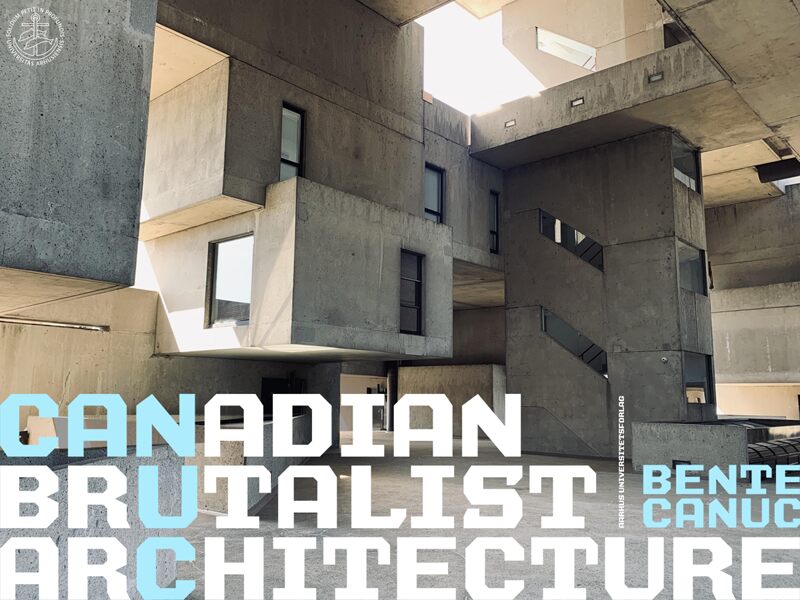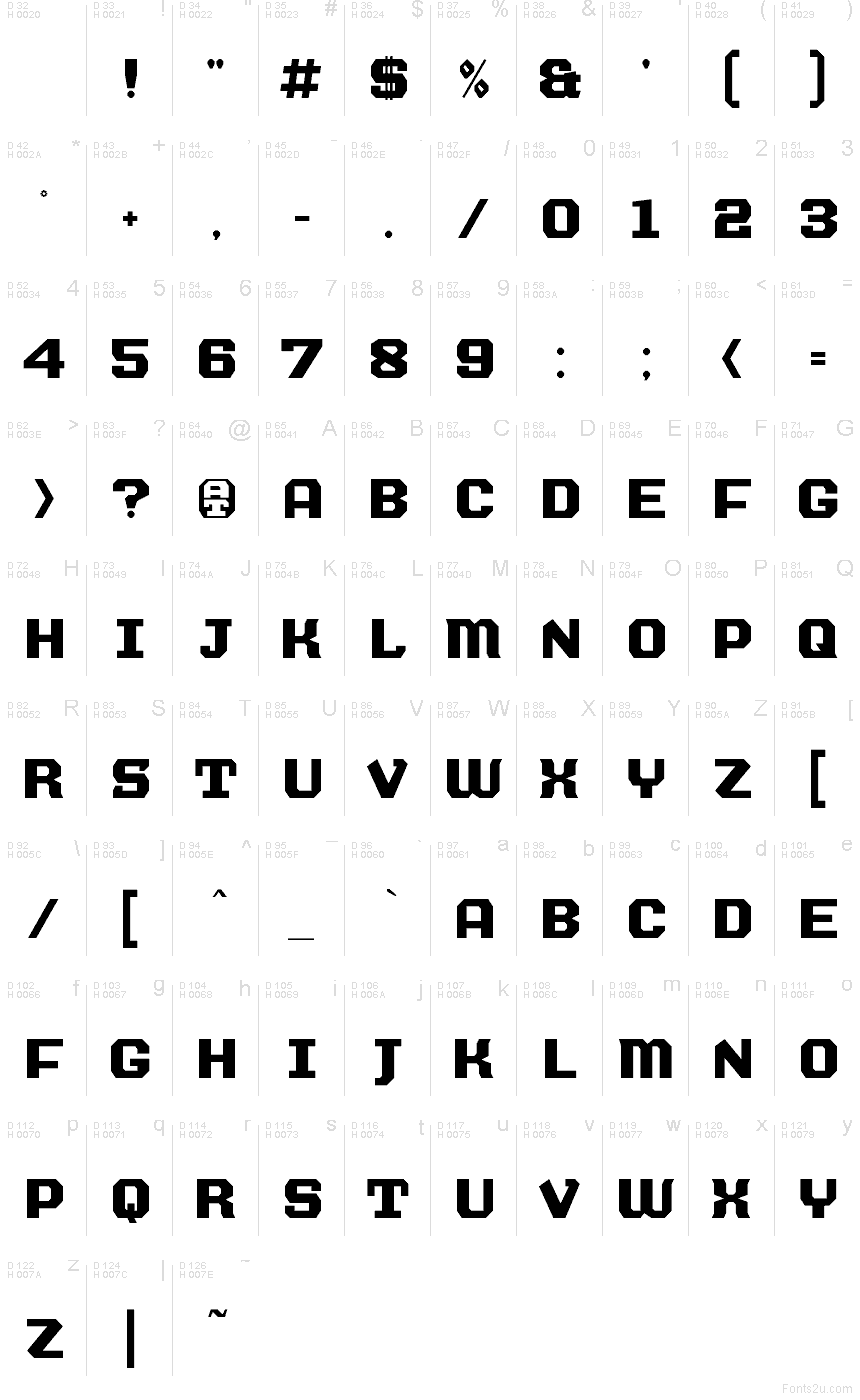
BOA Construktor von Tup Wanders ist eine kostenlose Old-School-Techno-Display-Schrift, die aus klobigen, gefasten Versalien besteht. Die Buchstaben wirken wie aus massiven Blöcken geschnitten, mit quadratischen Rundungen und gekappten Ecken, was der Schrift einen strengen, retro-futuristischen Rhythmus verleiht, statt eines glatten Sci-Fi-Looks.
Sie passt hervorragend zu Spiele-Logos, Plakat-Headlines, Plattencovern, Sport-Branding und Titelkarten, bei denen ein kurzes Wort einen harten, mechanischen Punch braucht. Da es eine kostenlose Schrift ist, eignet sie sich auch perfekt für Cover-Texte, Monogramme und Event-Grafiken, da die kompakten, achteckigen Formen selbst kurze Begriffe entschlossen und gewichtig wirken lassen.
Es wurde kein spezieller Kleinbuchstabensatz erstellt, da Schriften wie diese meist in VERSALIEN verwendet werden; die verfügbaren Kleinbuchstaben enthalten jedoch einige Variationen.